Seguimos con nuestra tanta de reviews de rotuladores para lettering y hoy os vamos a hablar de uno de nuestros favoritos. Se trata de los rotuladores Kuretake Metallic. También los podéis encontrar con el nombre más específico de Zig Fudebiyori Metallic Brush Pen. Casi todas las marcas de rotuladores que tenemos en el mercado son japonesas (Pentel, Sakura, Tombow, Pilot…) y Kuretake es otra de ellas. Aunque Kuretake quizás no es no tan conocida como las anteriores, es una marca de gran calidad, tanto en el material con el que están fabricados los rotuladores, como en las tintas que emplean. Hoy os vamos a hablar de unos de los modelos de rotulador que más éxito tienen, los metallic o metálicos.
Características rotuladores Kuretake Metallic
Ahora os vamos a detallar las características que hacen de los rotuladores Kuretake Metallic una gran opción para caligrafía y lettering
- Punta de pincel flexible y resistente con la que se consiguen trazos finos y gruesos.
- Colores metálicos brillantes y que reflejan la luz de distintas formas.
- Tinta con base al agua, sin ácidos, resistente a la luz, sin olor y sin xileno.
- Disponible hasta en 9 colores metalizados: dorado, plateado, violeta, verde, verde claro, azul, rojo, negro y bronce.
- Perfectos para caligrafía y lettering, aunque también para ilustración.
Prueba de rotuladores Kuretake Metallic
En las siguientes imágenes podéis ver unas pocas muestras que hemos hecho utilizando los rotuladores Kuretake Metallic, algunas sobre papel blanco de Rhodia y otros sobre cartulina lienzo de Clairefontaine y cartulina negra de Canson. Cabe decir que nuestra cámara no refleja la grandeza de este producto y su increíble brillo metalizado, aunque lo hemos intentado.
- Sobre cartulina efecto lienzo de Clairefontaine queda así:
- Sobre cartulina negra Canson, queda así:
- Sobre papel blanco de Rhodia queda así:
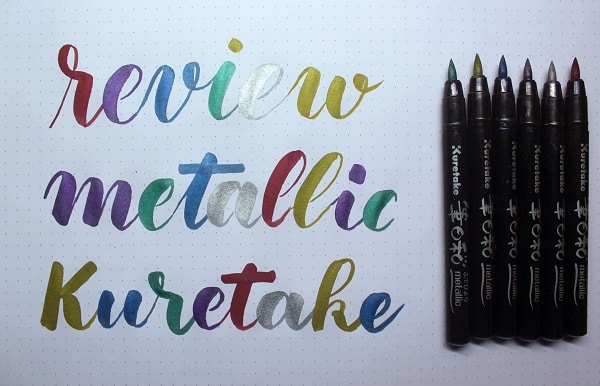
EJEMPLOS DE HAND LETTERING CON ROTULADORES KURETAKE METALLIC
Ahora os vamos a mostrar tres ejemplos de hand lettering con rotuladores Kuretake Metallic creados por @julielligraphy en los que combina los rotuladores metálicos rojos, verdes y azules con otros para crear ciertos efectos muy característicos del lettering.